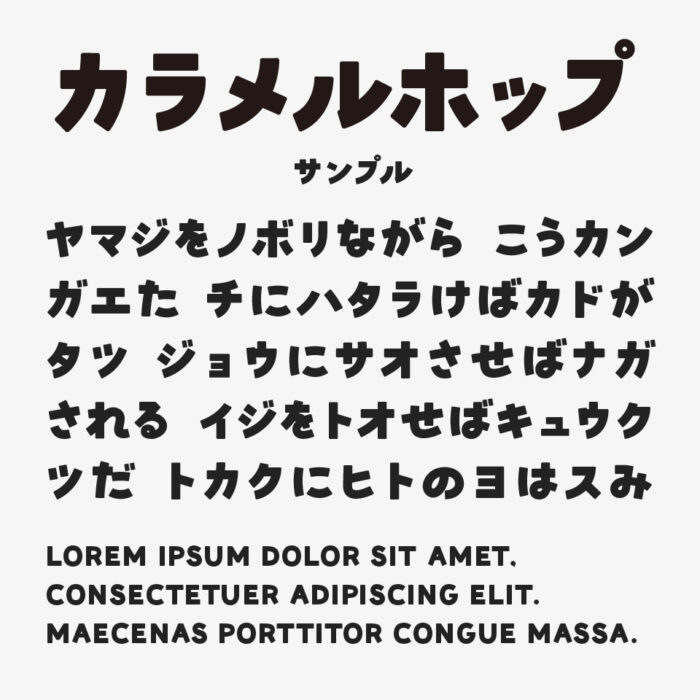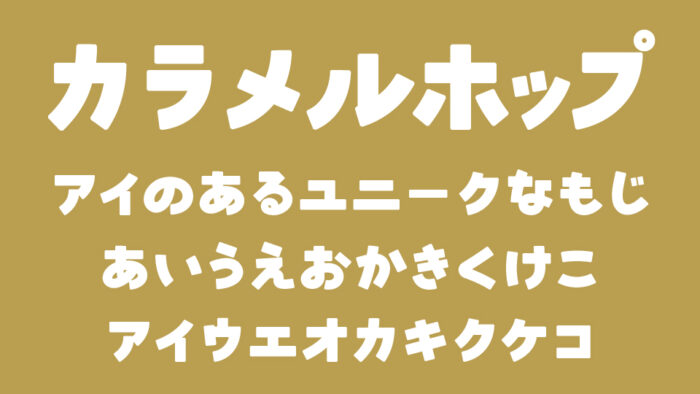
カラメルホップは、ポップで軽快感がありながら、太めでどっしりとした存在感のあるポップなデザインフォントです。
文字の角が少しだけ丸みを帯びており、硬すぎず、やわらかすぎない絶妙なバランスのデザインです。
ポップでかわい雰囲気を持ちながらどっしりとしたインパクトがあるので、タイトルやテロップ・サムネイルなど幅広く活躍できそうなフォントです。
収録文字は、ひらがな・カタカナ・英数字・記号が収録されています。